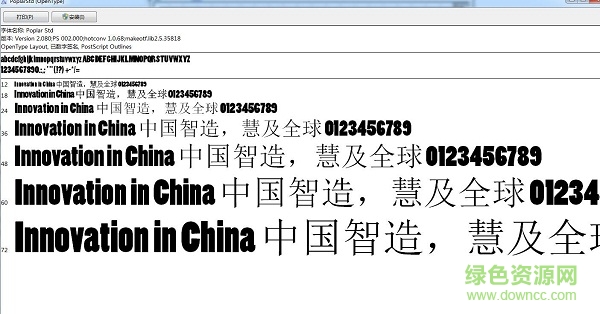
poplar std字體是一款渾厚得體的英文粗體字體,字體的結(jié)構(gòu)嚴(yán)謹(jǐn)端正,構(gòu)思精巧,符合字體構(gòu)形規(guī)律,適合用在廣告或是文章標(biāo)題處,歡迎需要的朋友在綠色資源網(wǎng)下載!
保持著無(wú)襯線(xiàn)字體的共有特點(diǎn),筆畫(huà)粗壯有力,結(jié)構(gòu)方正飽滿(mǎn),橫豎筆畫(huà)粗細(xì)比較接近,兩端平直,加鋒較??!